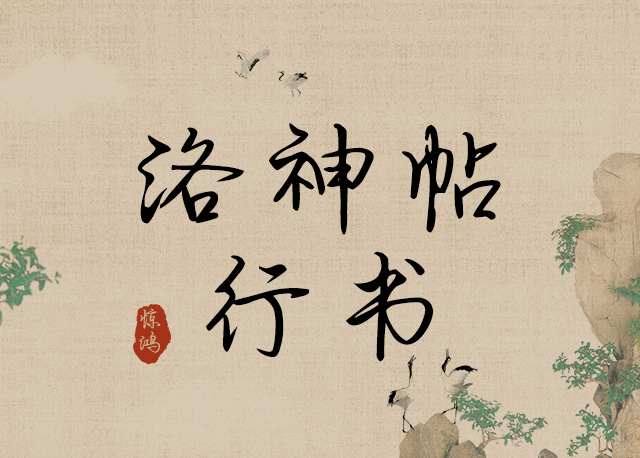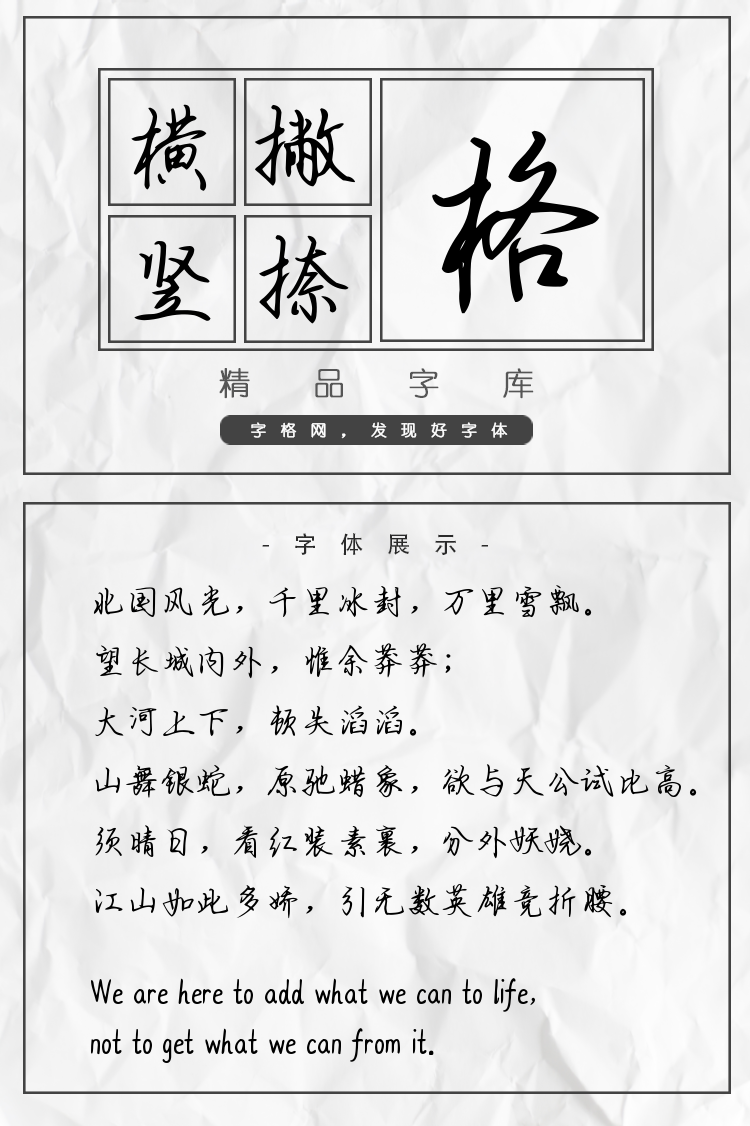
Aa洛神帖行书
字体说明:Aa洛神帖行书字体是一款可商用的毛笔书法,英文手写,手写体字体,该字体包含6763个中文、字母、符号和数字,具有充满力量、大气、豪放、稳重、手写风、古典 的风格,可以满足您设计上的各种需求,该字体主要用于电商、广告、视频影视、海报企宣、书籍 等场景, 您不但可以在字格网下载Aa洛神帖行书,同时还有众多毛笔书法字体、创意字体等可供选择!